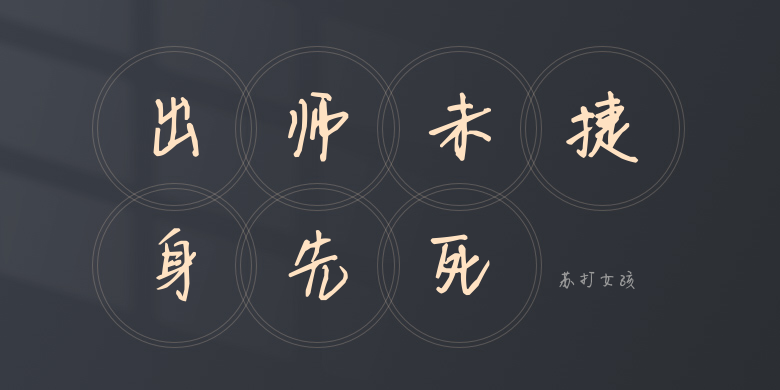
苏打女孩
苏打女孩,这款字体结构工整、笔画清晰,兼顾美观与易读性,适用于标题、正文、海报、包装、LOGO 等多种场景。字形优雅稳定,风格百搭耐看,适配日常排版与创意设计,让文字呈现更舒适、更具质感。苏打女孩一笔一画,皆是细节,以均衡的比例、流畅的线条打造舒适视觉体验,字形端正大气,风格简约现代。无论是商业设计、品牌宣传还是日常排版,都能轻松驾驭,让文字更有格调与力量。苏打女孩字体下载。